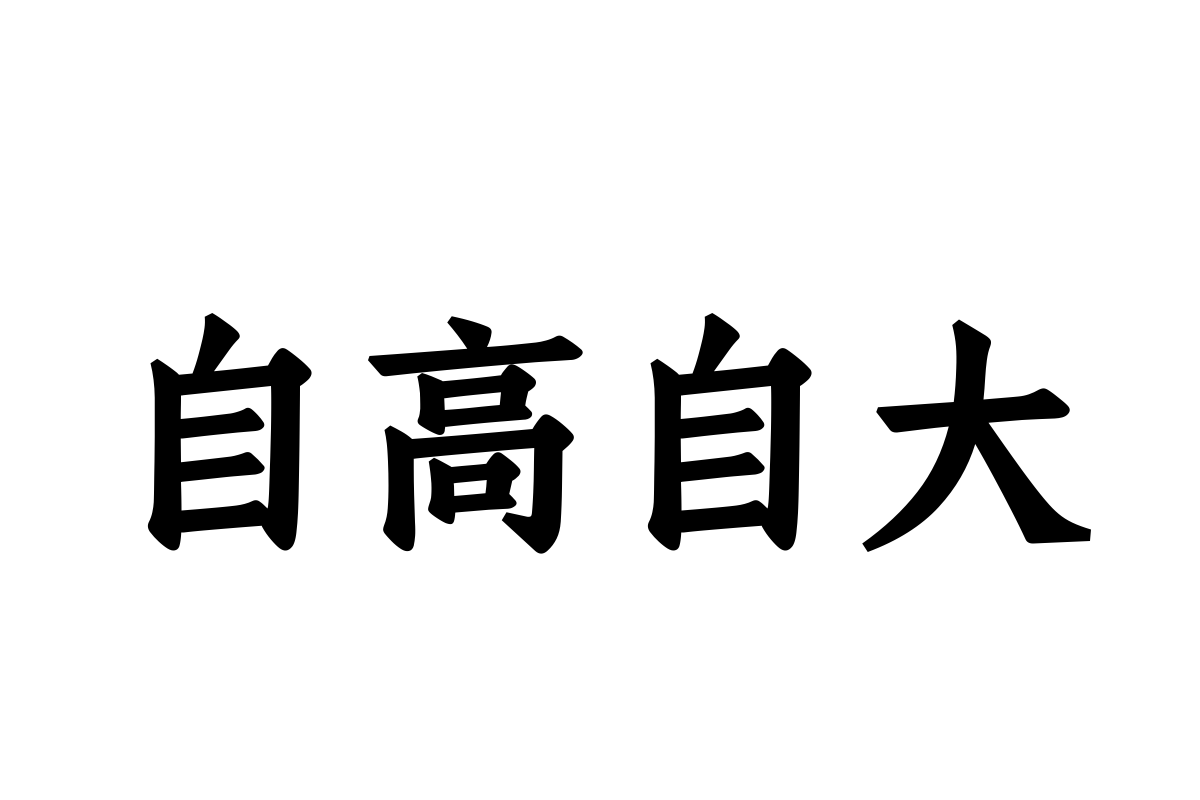
汉仪书仿95s是一款具有现代感的中文字体。它的特点是笔画流畅,字形简洁大方,适合用于标题、正文等需要清晰易读的场合。这款字体的设计灵感来自于传统的书法艺术,但又融入了现代审美的元素,使得它在保留传统韵味的同时,也不失时尚感。
汉仪书仿95s的笔画粗细适中,既有力度又不失柔和,既适合正式的文件,也适合日常的书写。它的线条流畅,没有过多的装饰性细节,让人一眼就能抓住重点。同时,这款字体的字形结构紧凑,不会显得拥挤,让人在阅读时能够轻松地获取信息。
总的来说,汉仪书仿95s是一款非常适合现代办公环境的中文字体。无论是用于网页设计、平面设计还是其他需要文字表达的场景,它都能展现出独特的魅力。